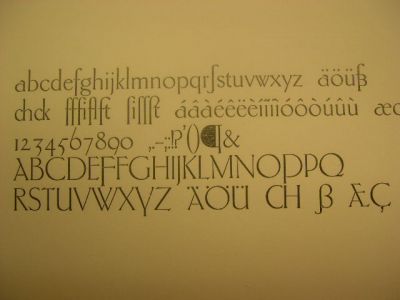
Scharf und versal und dennoch ein S?
ich habe mich bisher vor der Diskussion gedrückt und die Debatte mit einer Mischung aus Verwunderung und Amüsement verfolgt. Nun bin ich aber doch neugierig geworden.
Ich selbst kann dem Gedanken an ein versales ß wenig abgewinnen. Zum Einen wünsche ich mal, nach der Erfahrung mit der Rechtschreibreform viel Glück mit einer solchen Schreibform. Ich kann mir dabei nur zwei Resultate vorstellen: das versale ß wird von der Öffentlichkeit ignoriert oder die Verantwortlichen werden an einer Straßenlaterne aufgehängt.
Ich würde mich an die Verwendung eines versalen ß halten, so es zum Standard würde, nach meiner Meinung gefragt lehne ich es aber bisher ab. Zum Einen stellt sich mir die Frage ob es das in der Geschichte der lateinischen Buchstaben schon einmal gegeben hat, dass sich aus einer Ligatur zweier Gemeinen eine Versalie gebildet hat.
Dies ist jedoch nicht der Grund für meine Ablehnung. Die rührt eher daher, dass mir noch keine überzeugende ß-Versalie unter die Augen gekommen ist. Wenige andere Buchstaben haben dem Schriftgestalter so viel Freiraum für Kreativität gegeben. Und dieser Freiraum wurde auch genutzt. So haben wir eine breite Vielfalt an Varianten der Form des ß.
Die versalen ß die ich bisher gesehen habe gingen ohne weiteres als Variante des gemeinen ß durch. Man muss schon ein Schriftkenner und Typophiler sein um ein solches neues versales ß von der gemeinen Gemeine zu unterscheiden.
Und so stellt sich für mich die Frage was für einen Sinn der ganze Aufruhr hat, wenn ein versales ß von einem gemeinen ß kaum zu unterscheiden ist? Wäre es da nicht einfacher die Regel, dass ein gemeines ß niemals in Versaltext vorkommen darf über Bord zu schmeißen und im Sinne einer einfacheren Handhabung drei gerade sein lassen?
Das sind jetzt rein typografische Überlegungen. Vom technischen Standpunkt betrachtet würde sich die Sache ja wohl ohnehin kaum durchführen lassen, denn es hieße, dass alle Schriften die wir heute verwenden – wums – Zwecklos wären. Wir könnten sie gleich neben den deutschen Tastaturen entsorgen. Denn ein versales ß in den unerreichbaren Tiefen einer OpenType-Schrift ist doch absurd, oder?
Mich erinnert das Ganze etwas an den oft beschworenen ›Talk im Turm‹, nämlich im Elfenbeinturm.
Ich bin schon auf eure Argumente gespannt und würde mich ja auch überzeugen lassen, wenn es treffende wären.
Gibt es oder gab es in Österreich eigentlich diesbezüglich abweichende Regeln? In der Schweiz gab es das ß ja ohnehin nie …
Ich sehe es ganz ähnlich wie Du: Es ist eine ebenso interessante wie faszinierende Diskussion unter Fachleuten und Maniacs (die wir alle sind), von der die Außenwelt wohl kaum je besonders Kenntnis nehmen wird. Vor allen Dingen wäre ja die ganze ß-Reform für die Katz, da der Durchschnittsbürger wohl kaum den Unterschied zwischen einem kleinen und einem versalen ß überhaupt auszumachen vermöchte …
Gibt es oder gab es in Österreich eigentlich diesbezüglich abweichende Regeln? In der Schweiz gab es das ß ja ohnehin nie …
Nein. Österreich folgt in vielen Belangen dem Vorbild Deutschlands. Es gibt ein paar Worte die im Duden als typisch österreichisch ausgezeichnet sind, aber im Grunde ist Deutsch und Österreichisch dasselbe (nur die unsägliche neue-Rechschreibung-Diskussion ist relativ spurlos an uns vorbei gegangen).
Die Schweizer orientieren sich traditionsgemäß auch sehr stark nach Frankreich. Das sieht man auch in der Typografie ganz gut: «Französische Anführungszeichen wie von den Franzosen angewendet».
Aber ich bin mir sicher, da könnte eine Mitleser aus der Schweiz mehr dazu sagen.
Locarno liegt in der Schweiz …
War mir gar nicht bewusst (dass du Schweizer bist).
Schönes Bild. Hast das grad gemacht?
So die Seenlandschaft Tessin, Italien – das wäre ja mein Traum Lebensort. Berge, Wasser, Wäler – alles was wir hier auch haben, nur mit mehr Sonne. :-)
... In der Schweiz gab es das ß ja ohnehin nie …
Du meinst mit nie wohl ab den 30er Jahren?
Bitte unterschlag nicht 700 Jahre Benutzung des ß in der detuschsprachigen Schweiz mit 70 Jahren Nichtbenutzung.
An Formgebung. Die ganze Thematik wurde doch in den Beiträgen schon hoch und runter mit allen Pro- und Contra Punkten diskutiert, darunter auch deine Fragen.
Du meinst mit nie wohl ab den 30er Jahren?
Bitte unterschlag nicht 700 Jahre Benutzung des ß in der detuschsprachigen Schweiz mit 70 Jahren Nichtbenutzung.
Gehe ich Recht in der Annahme, dass du mich und nicht Henning (Formgebung) gemeint hast? Muss ich mich wohl entschuldigen. Ich hatte gar nicht daran gedacht, diesbezüglich in den alten Beiträgen zu stöbern.
Deine Beiträge lese ich sehr gerne. Sie machen deutlich, wo die Grenze zwischen Fachmann und halbinformiertem ‹Kenner› liegt.
..., sondern mich auf die Frage von Designworker konzentriert.
Deine Beiträge lese ich sehr gerne. Sie machen deutlich, wo die Grenze zwischen Fachmann und halbinformiertem ‹Kenner› liegt.
Ich bin neugierig: Auf welcher Seite der Grenze würdest du Roman sehen.